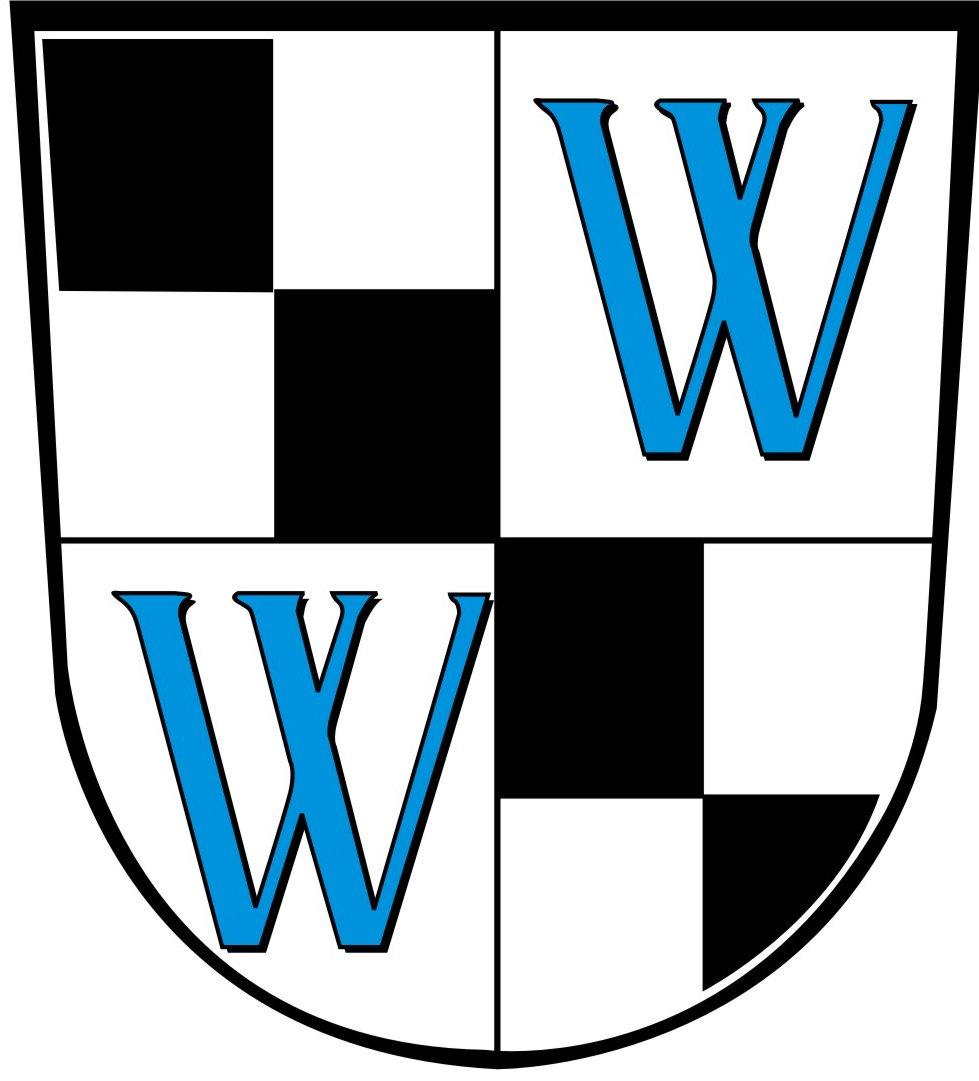
Suche die Serifen Schrift eines Gemeindewappens
ich bin auf der Suche nach dieser Serifen Schrift, die in einem Gemeindewappen verwendet wurde.
Diese Vorlage stammt von der Gemeinde. Wer das ursprünglich erstellt hat ist nicht mehr nachzuvollziehen, ebenso das Entstehungsjahr.
Erkennt zufällig jemand diesen Font?
Ich suche diesen oder gerne auch ähnliche Fonts, welche im Optimalfall kostenlos sind.
Hupps Abbildung, die in Unkenntnis der farbigen Zeichnung von 1581 die Buchstaben blau in Silber wiedergibt, diente als Vorlage für das Dienstsiegel von 1938. An dieses knüpfte neuerdings die ministerielle Bestätigung an.
Beschreibung:
Geviert;
1 und 4: in Silber der schwarze gotische Großbuchstabe W;
2 und 3: geviert von Silber und Schwarz
Gotisch 8-):-?
Genauere Beschreibungen sind in der Heraldik auch relativ egal, weshalb der Buchstabe auch nicht unbedingt einer Font entstammen muss und auch die oben genannte Bezeichnung „blau” als Farbe für die Wappenbeschreibung vollkommen ausreichend ist. (Selbst für den relativ präzise festgelegten Bundesadler gilt, dass „[d]ie künstlerische Gestaltung für jeden besonderen Zweck vorbehalten [bleibt]“ [Quelle].
Wenn es also um das Wappen geht, kann man die Buchstaben auch durch Buchstaben einer anderen Font ersetzen, ohne dass es im heraldischen Sinne ein anderes wäre, man vergleiche etwa auch die Ausführungen von Bernhard Peter zu diesem Thema (bzw. zum Thema Variabilität in Wappen im Allgemeinen). Daher wird man wohl auch in offiziellen Beschreibungen des Wappens nichts zu diesem Thema finden…
Das mag früher mal gegolten haben. Heute gibt es aber zu praktisch jedem amtlichen Wappen ein bildliches Muster (oder mehrere, wenn es mehrere Wappenvarianten gibt). Jedem Gestalter, der ein kommunales Wappen nur nach den Vorgaben der Blasonierung gestaltet und das bildliche Muster dabei ignoriert, würde der kommunale Auftraggeber das um die Ohren hauen.